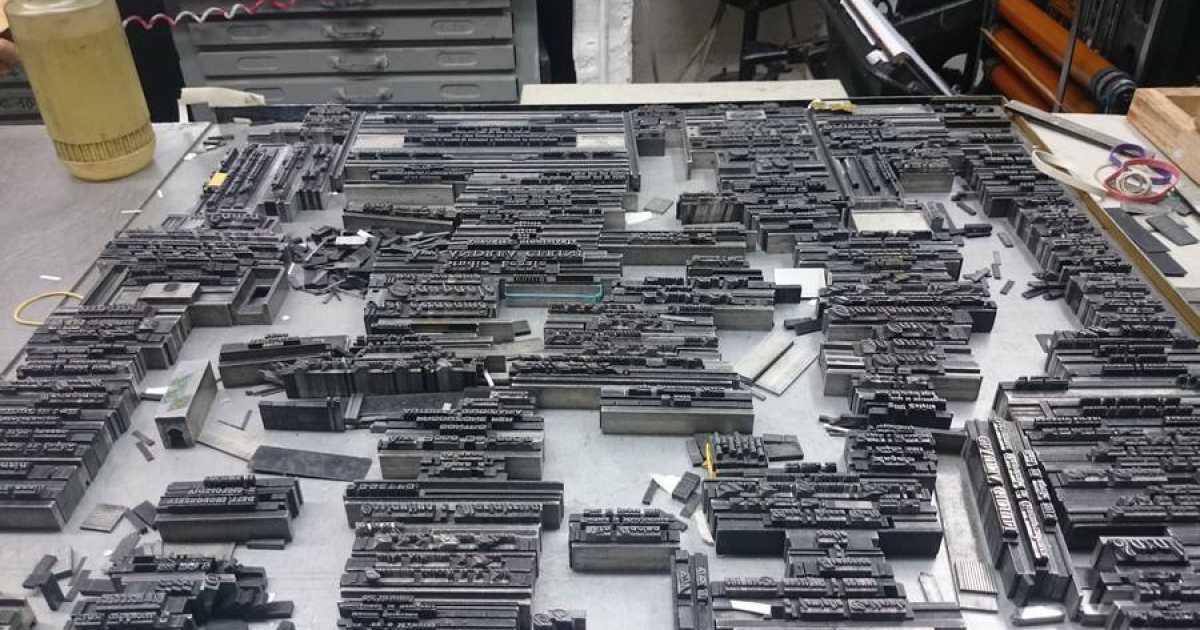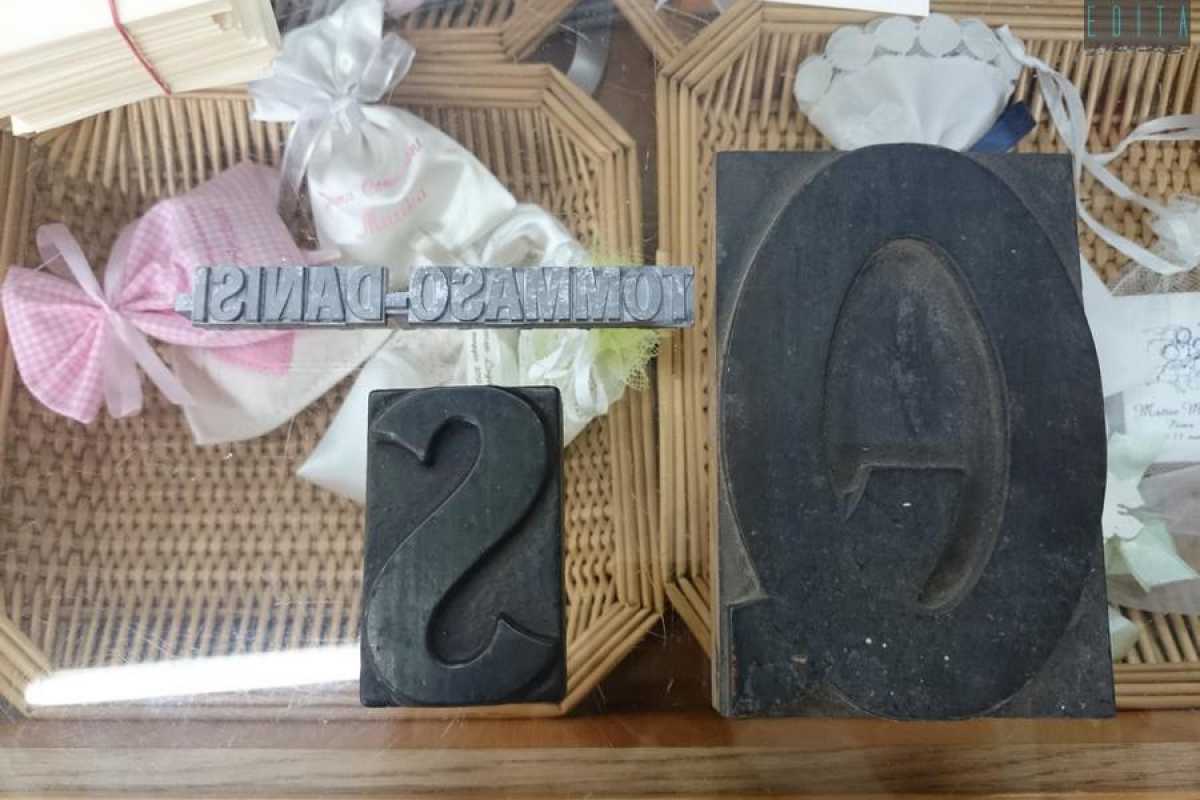
La tipografia che stampa ancora con i caratteri mobili: «A Bari dal 1934»
BARI - La sua invenzione risale al 1455 ed è stata attribuita a Gutenberg, anche se si dice che in Asia c'era chi la praticava già dall'XI secolo. Stiamo parlando della stampa a caratteri mobili che, nonostante l'avvento della stampa digitale, riesce ancora a sopravvivere, anche a Bari. La "Tipografia del commercio" di Lecce, di cui avevamo parlato in un articolo precedente, non è infatti l'unica in Puglia a mantenere viva l'antica tecnica. Nel capoluogo i caratteri mobili resistono ancora nella storica tipografia Danisi attiva dal 1934 e che solo per pochi anni non ce l'ha fatta a rientrare nella nostra lista di negozi antichi baresi, dato che il limite temporale che ci eravamo fissati per la nostra ricerca era il 1930.
Ubicata in via Davanzati, nei pressi di Piazza Umberto, la tipografia si presenta oggi in una veste rinnovata. A prima vista infatti non si direbbe che il negozio abbia addirittura più di ottant'anni. Recente è l'insegna blu e rossa con il nome dell'azienda che sovrasta l'ingresso e al passo con le nuove esigenze i numerosi oggettini ricordo esposti in vetrina e sugli scaffali di vetro. Solo una volta entrati e dopo aver scambiato qualche parola con la proprietaria, iniziamo a respirare l'atmosfera di un posto che nella sua apparente modernità ha invece tanto da raccontare.
«L'azienda nasce in realtà nel 1924 a Palo del Colle per mano di mio padre Tommaso Danisi che dopo dieci anni aprì una sede anche a Bari- racconta la 72enne Giovanna Danisi -. La sede originaria era sempre in via Davanzati, ma al numero 28, in un palazzo antico che una volta abbattuto ci costrinse a traferirci nel 1959 nell'attuale edificio».
Alla morte di Tommaso nel 1966, l'attività fu ereditata dai suoi quattro figli per poi passare definitivamente nel 1980 sotto la guida di Giovanna che insieme con suo marito Domenico Milella ne divenne la proprietaria. A continuare la tradizione di famiglia è subentrata in società, nel 1996, anche la figlia maggiore dei due, Lucia Milella.
Basta scendere le scale e raggiungere il laboratorio al piano inferiore per scoprire il tesoro che la famiglia Danisi da decenni custodisce (vedi foto galleria). Ad accoglierci il suono degli strumenti da lavoro in funzione, il profumo della carta e alcuni dei macchinari storici ancora oggi utilizzati. Ce ne sono addirittura due risalenti al 1800, che Tommaso Danisi acquistò nei primi anni di vita della tipografia. E’ possibile notare l'inchiostro che passa attraverso i rulli sul carattere e il pedale con cui la macchina viene messa in funzione.
Su un tavolo da lavoro non passano inosservati i caratteri mobili tipografici: tanti blocchetti metallici con la lettera in rilievo incastrati secondo un ordine ben preciso e che dopo la stampa vengono scomposti per essere utilizzati in una nuova combinazione. Una procedura che richiede quindi pazienza ed estrema precisione, ma il cui risultato finale sarà ogni volta unico e mai uguale a quello precedente.
Negli anni sono state tante le tecniche che si sono succedute e variegati i prodotti realizzati con questi macchinari, anche se ormai fanno parte del passato. «Durante gli anni della Seconda guerra mondiale mio padre non fu chiamato a combattere ma restò in tipografia a occuparsi della stampa di registri comunali e scolastici o di biglietti ferroviari», ricorda Giovanna.
Negli anni 50-60 invece si stampavano, con caratteri mobili giganti di metallo o di legno, manifesti di ogni tipo: il formato massimo era 1x70m. Il pezzo forte della tipografia erano però i calendari, dotati dei caratteristici blocchetti con i fogli numerati che si sfogliavano giorno per giorno e su cui venivano applicate immagini colorate. Un'epoca quella dei calendari che però non è più ritornata. «Ma negli anni 70-80 realizzavamo cartoncini colorati su cui venivano stampati dei caratteri stravaganti e insoliti e che esistevano solo sotto forma di matrici - racconta la donna-. Ogni cliente in questo modo aveva la possibilità di scegliere il carattere che più si addiceva alla circostanza e creare così biglietti, soprattutto d’invito, personalizzati. Eravamo gli unici in città a creare questo genere di lavori».
Queste tecniche però durarono solo pochi anni, visto che già a partire dagli anni 90 il computer entrò con prepotenza in tipografia, dettando modi e tempi di produzione. Ad oggi solo una parte della produzione Danisi si basa ancora sui caratteri mobili mentre il resto ha dovuto adeguarsi all'evoluzione del mercato. I caratteri mobili vengono utilizzati prevalentemente per un certo tipo di partecipazioni nuziali o per biglietti personalizzati e sono rivolti soprattutto a chi ne richiede una quantità ridotta. Anche se la differenza rispetto alle stampe digitali è evidente: le lettere non sono unite, il colore è pieno, la pressione sulla carta non è omogenea. Di fatto i caratteri mobili conferiscono quel quid di prestigio e fascino che le comuni carte stampate non possiedono.
«E comunque alcune produzioni possono essere eseguite solo attraverso questa tecnica – sottolinea orgogliosa Giovanna-. Ad esempio le pergamene con la benedizione apostolica che vengono richieste al Papa in occasione dei matrimoni, spesso arrivano con degli errori. Ebbene, l'unico modo per correggerle è utilizzare le vecchie macchine. Altro che computer, con quelli non lo si potrebbe mai fare».